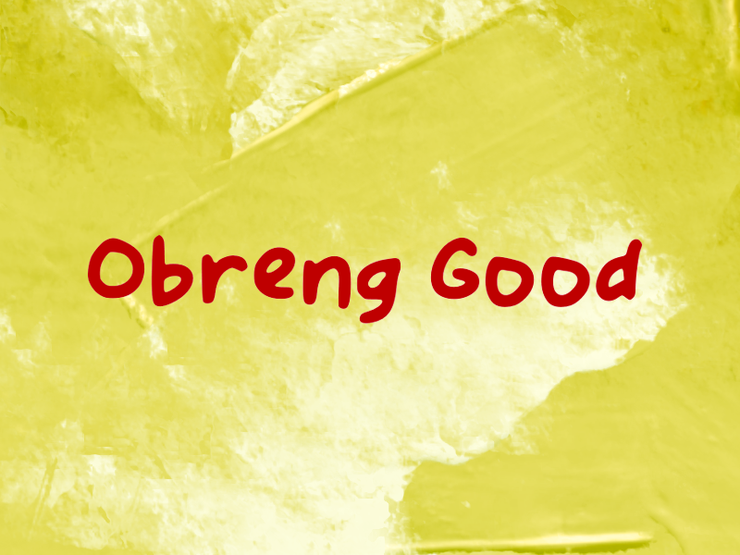
Obreng Gut Stilvoll Modern Elegant Dekorativ Englisch Schriftart
Obreng Good ist eine kreative, moderne, dekorative englische Schrift mit einzigartigen Strichdetails und ausgewogenen Glyphenstrukturen. Mit glatten Kurven und stilvollen Konturen kombiniert sie lässige Persönlichkeit mit eleganter Textur und präsentiert einen frischen und auffälligen visuellen Stil. Diese vielseitige Schrift ist ideal für Markenlogos, Modeposter, Web-Schlagzeilen, E-Commerce-Banner, Produktverpackungen, Social-Media-Grafiken und dekorative Typografie. Komplett mit Groß- und Kleinbuchstaben ist sie hochgradig skalierbar und lässt sich leicht an Farben, Größen und Layouts anpassen, ohne ihre einzigartigen Designmerkmale zu verlieren. Geeignet für Grafikdesigner, Kreativstudios und kommerzielle Markenprojekte, um verschiedenen visuellen works.Free für den kommerziellen Gebrauch einen exklusiven, stilvollen Charme zu verleihen / Kein Copyright 1